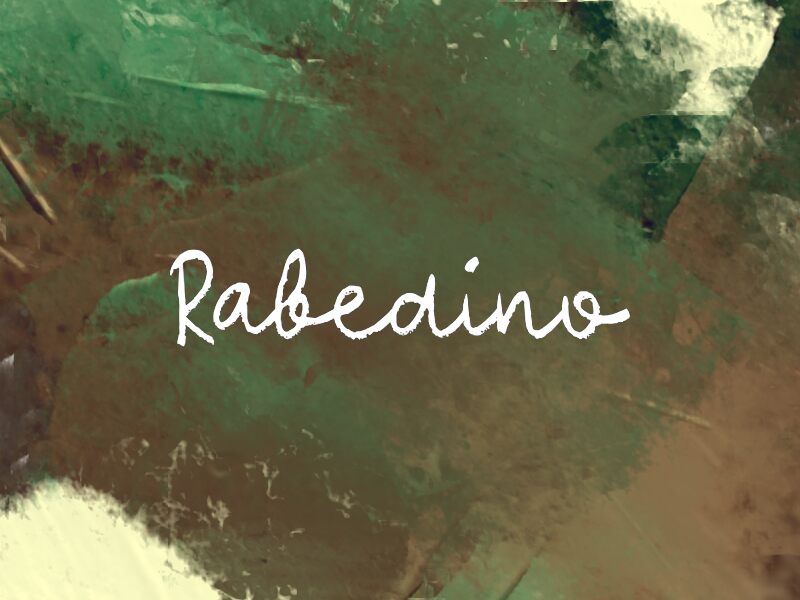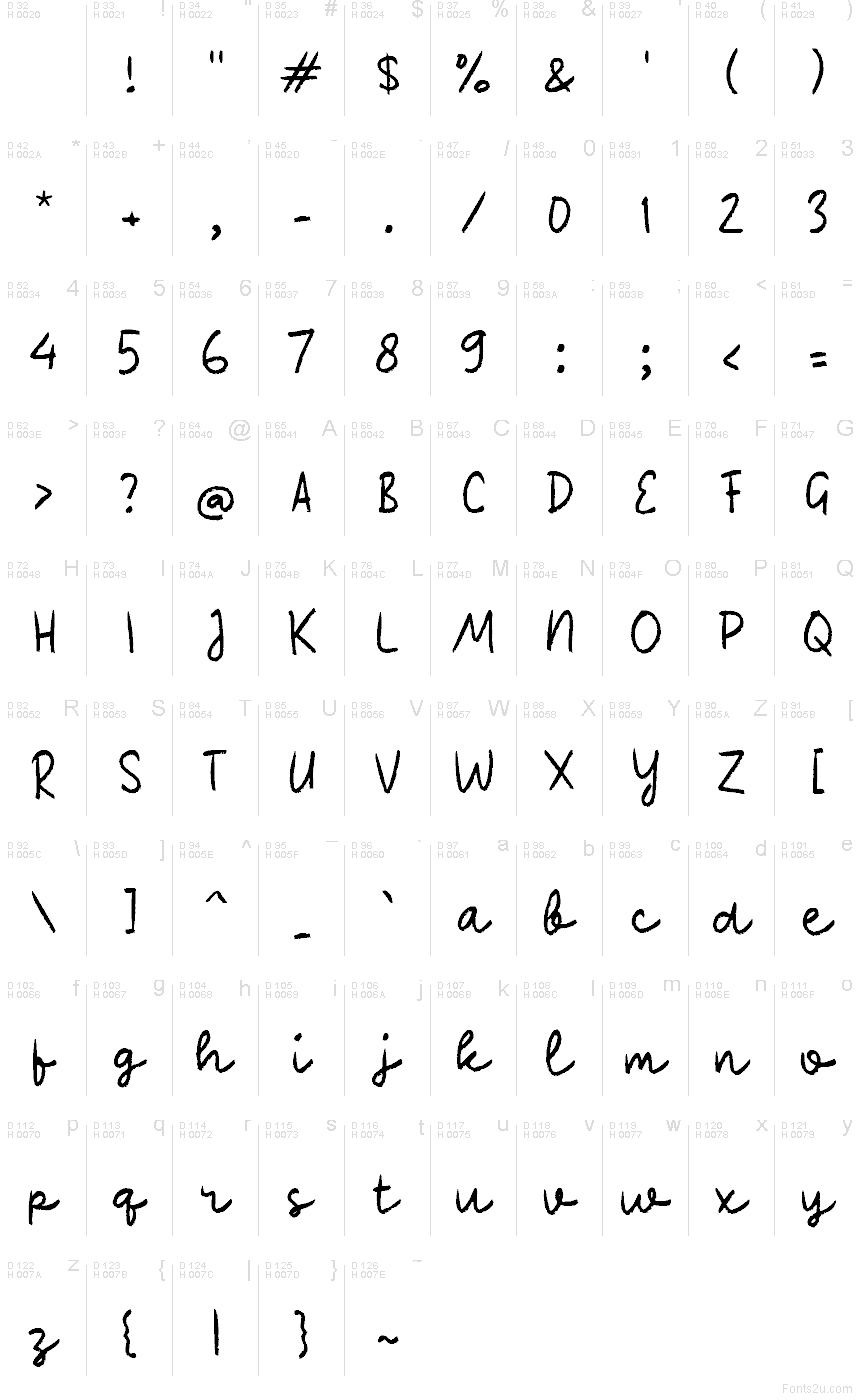
Rabedino
Rabedino od wep je bezplatné ručně psané písmo, jehož rychlý, plynulý rytmus působí jako skica fixem spíše než jako uhlazená kaligrafie. Široké tahy, drsnější hrany a dlouhá propojení mu dodávají neformální dynamiku, která v návrhu působí konzistentně.
Díky tomu je Rabedino přirozenou volbou pro nadpisy plakátů, menu v kavárnách, obaly produktů, citáty na sociálních sítích nebo neformální branding, kde působí ručně psaná poznámka mnohem uvěřitelněji než úhledná kaligrafie. Mírně hrubší textura brání tomu, aby font při větším měřítku působil příliš sterilně, a dodává pozvánkám nebo grafice ve stylu scrapbooku osobnější nádech.